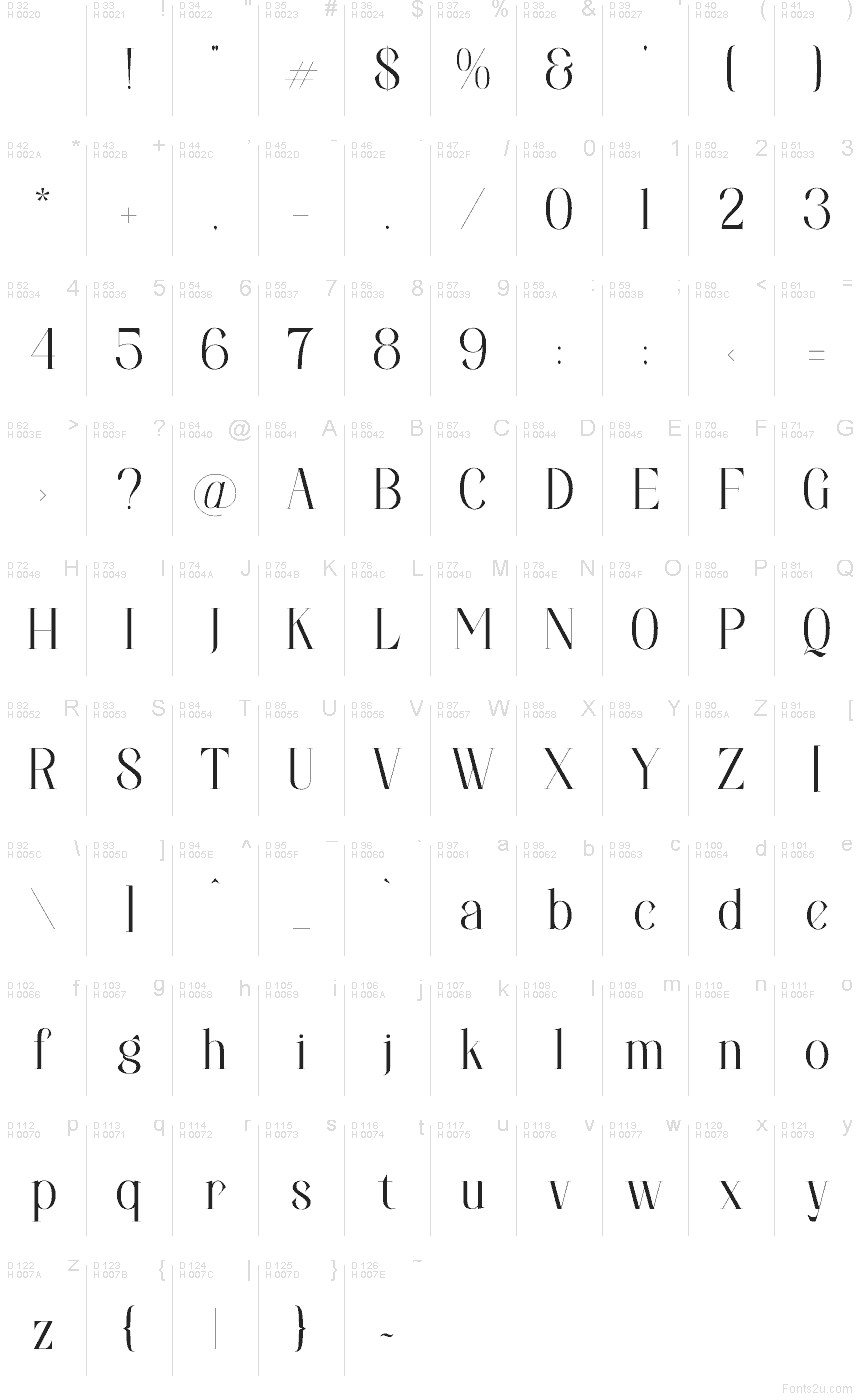
Flare Majestic
Flare Majestic od Risma Type je bezplatné dekoratívne pätkové písmo. Dlhšie, vzpriamené drieky pripomínajú stĺpy z lešteného kovu, zatiaľ čo ťahy sa zužujú do ihlovo tenkých liniek, ktoré pútajú zrak ako záblesk svetla. Hladké a veľkorysé krivky dodávajú každému slovu zmysel pre pohyb a vyváženosť, vďaka čomu titulky pôsobia elegantne a jemne dramaticky, nikdy však strnulo.
S Flare Majestic dodáte luxusný, redakčný nádych módnemu brandingu, obalom parfémov či kozmetiky, časopisom, plagátom, pozvánkam alebo logám. Tento bezplatný font vyniká vo väčších veľkostiach, kde jeho jemné kontrasty zostávajú ostré a čitateľné. V hlavnom texte ho skombinujte s jednoduchým geometrickým bezpätkovým písmom, aby bola sadzba čistá a nechala Flare Majestic vyniknúť v momentoch, keď potrebujete zaujať.